Đặc điểm của bộ font tiếng Nga full (Cyrillic)
Hệ chữ Cyrillic được sử dụng cho tiếng Nga và nhiều ngôn ngữ Đông Âu khác, sở hữu cấu trúc hình khối đặc trưng, mang lại cảm giác vững chãi và uy tín trong thiết kế đồ họa.
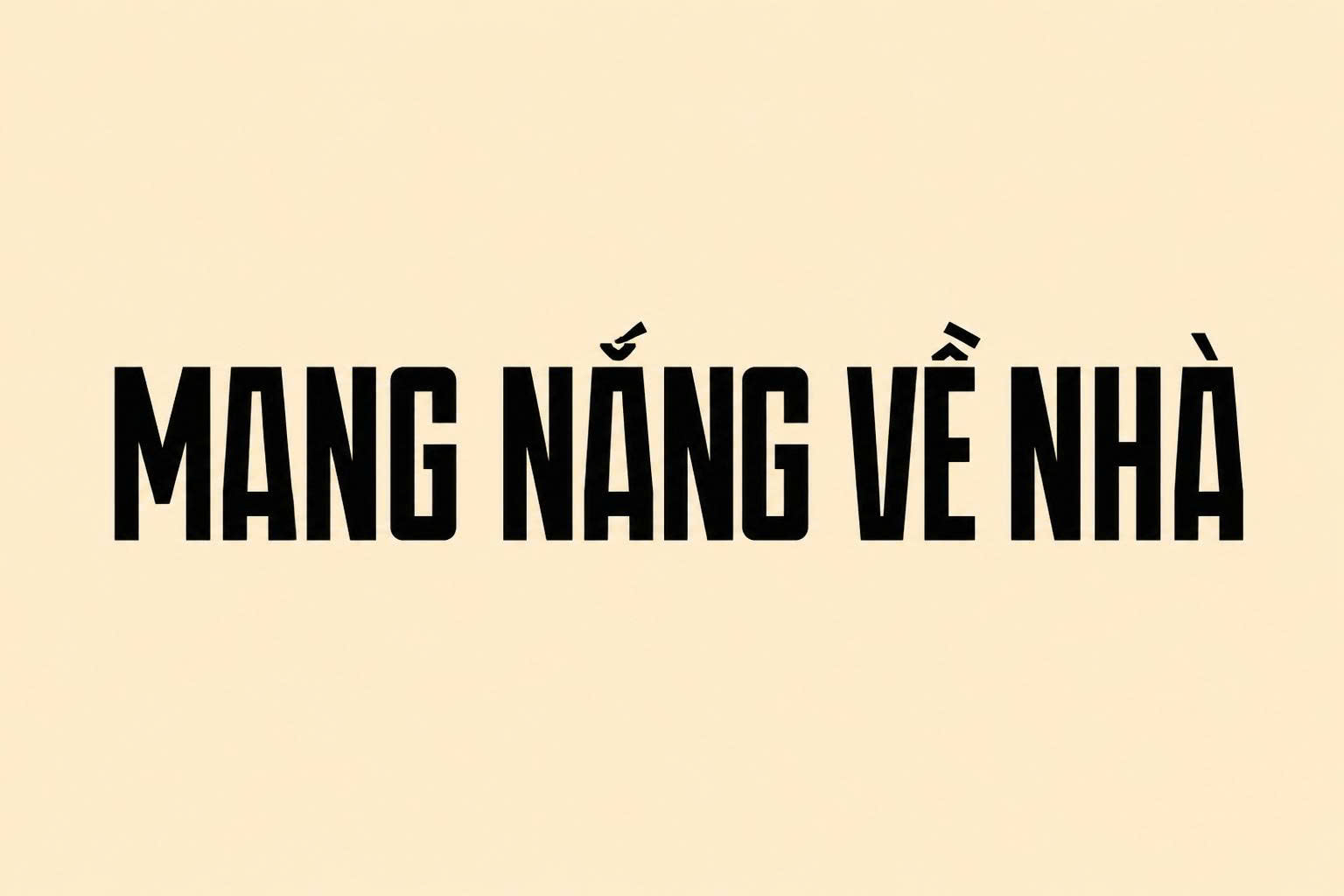
Hệ thống ký tự Cyrillic đặc thù
Bộ font tiếng Nga đầy đủ bao gồm các ký tự đặc biệt như “д”, “ж”, “щ”, “ю”… vốn không có trong hệ chữ Latinh. Khi thiết kế tem nhãn cho hàng xuất khẩu, việc sử dụng một bộ font “full” đảm bảo các thông tin kỹ thuật, bảng thành phần và hướng dẫn sử dụng được hiển thị chính xác 100%, tránh những sai sót pháp lý nghiêm trọng khi đưa sản phẩm ra thị trường quốc tế.
Tính tương thích đa ngôn ngữ (Multilingual Support)
Một bộ font cyrillic đầy đủ chất lượng cao thường được thiết kế theo chuẩn Unicode, hỗ trợ đồng thời tiếng Nga, tiếng Anh và tiếng Việt. Điều này cực kỳ quan trọng trong dàn trang bao bì song ngữ tại Việt Nam, giúp các khối văn bản đạt được sự đồng nhất về phong cách thiết kế (Typography Style), không bị hiện tượng “chữ đậm chữ nhạt” do phải dùng hai bộ font khác nhau.
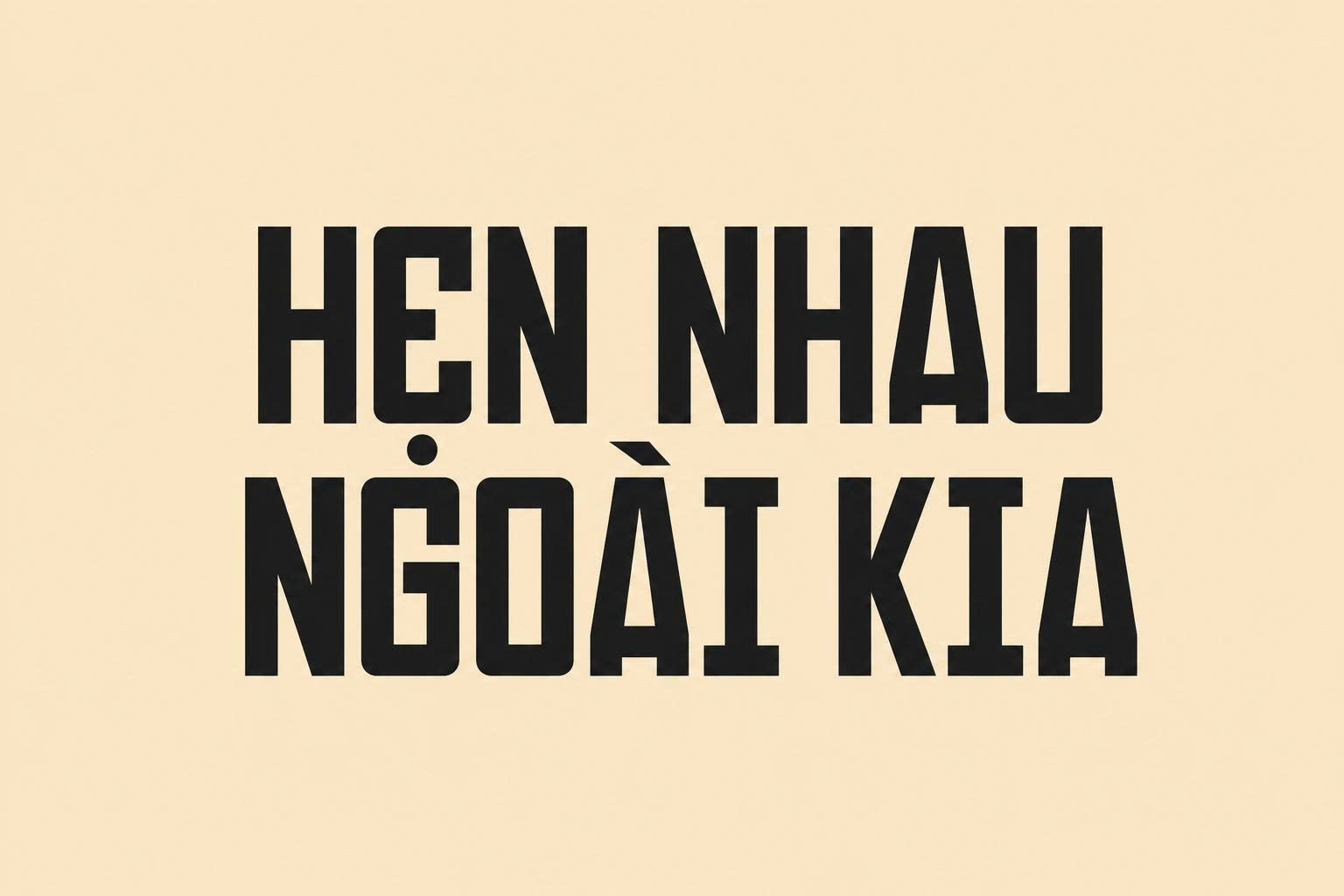
Tại sao cần sử dụng font tiếng Nga Việt hóa cho thiết kế bao bì?
Trong ngành sản xuất bao bì tại Doozypack.vn, chúng tôi thường xuyên xử lý các mẫu tem nhãn thực phẩm, mỹ phẩm xuất khẩu sang thị trường Nga. Việc sử dụng font tiếng Nga Việt hóa mang lại nhiều lợi ích:
- Đồng bộ nhận diện thương hiệu: Giúp tên thương hiệu và thông tin mô tả bằng tiếng Việt và tiếng Nga có cùng một diện mạo hiện đại hoặc cổ điển tùy theo định vị sản phẩm.
- Dễ dàng kiểm soát bố cục: Với phông chữ hỗ trợ cả hai ngôn ngữ, designer có thể căn chỉnh khoảng cách dòng (leading) và khoảng cách chữ (kerning) một cách chính xác trên toàn bộ nhãn mác.
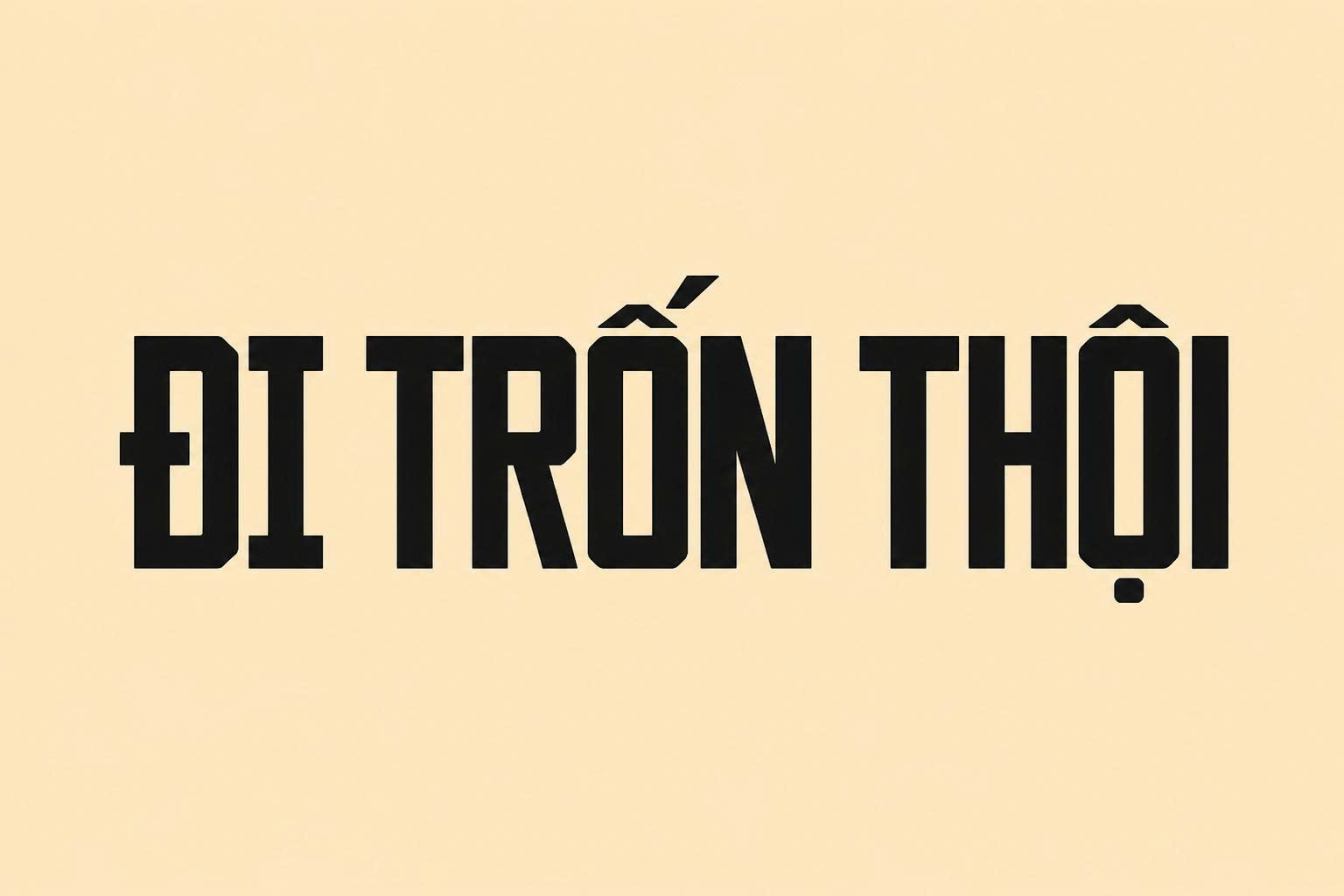
Doozypack.vn tổng hợp bộ thư viện font tiếng Nga đa dạng từ phong cách không chân (Sans-serif) hiện đại đến có chân (Serif) trang trọng, phù hợp cho mọi nhu cầu thiết kế.
| Nhóm Font | Đặc điểm thị giác | Ứng dụng đề xuất tại Doozypack.vn |
| Sans-serif Cyrillic | Hiện đại, minh bạch | Dùng cho bảng thành phần, mã vạch, thông số kỹ thuật. |
| Serif Cyrillic | Cổ điển, uy tín | Dùng cho tên sản phẩm cao cấp, nhãn rượu, hộp sâm. |
| Display Cyrillic | Nổi bật, cá tính | Dùng làm tiêu đề chính, slogan hoặc logo thương hiệu. |
Tư vấn từ chuyên gia: Khi thiết kế bao bì xuất khẩu, bạn nên ưu tiên các dòng Sans-serif (không chân) có độ dày trung bình (Medium). Đây là nhóm font an toàn nhất, đảm bảo người tiêu dùng bản địa dễ dàng đọc được thông tin ngay cả ở kích thước tem nhãn nhỏ.
- Hộp giấy quà tặng: Sự kết hợp giữa font tiếng Nga Việt hóa và kỹ thuật ép kim mờ tạo nên vẻ ngoài chuyên nghiệp cho các sản phẩm nông sản, cà phê xuất khẩu.
- Túi giấy doanh nghiệp: Tên công ty và địa chỉ in bằng font Cyrillic giúp tăng tính quốc tế và uy tín cho thương hiệu khi tham gia các hội chợ thương mại toàn cầu.
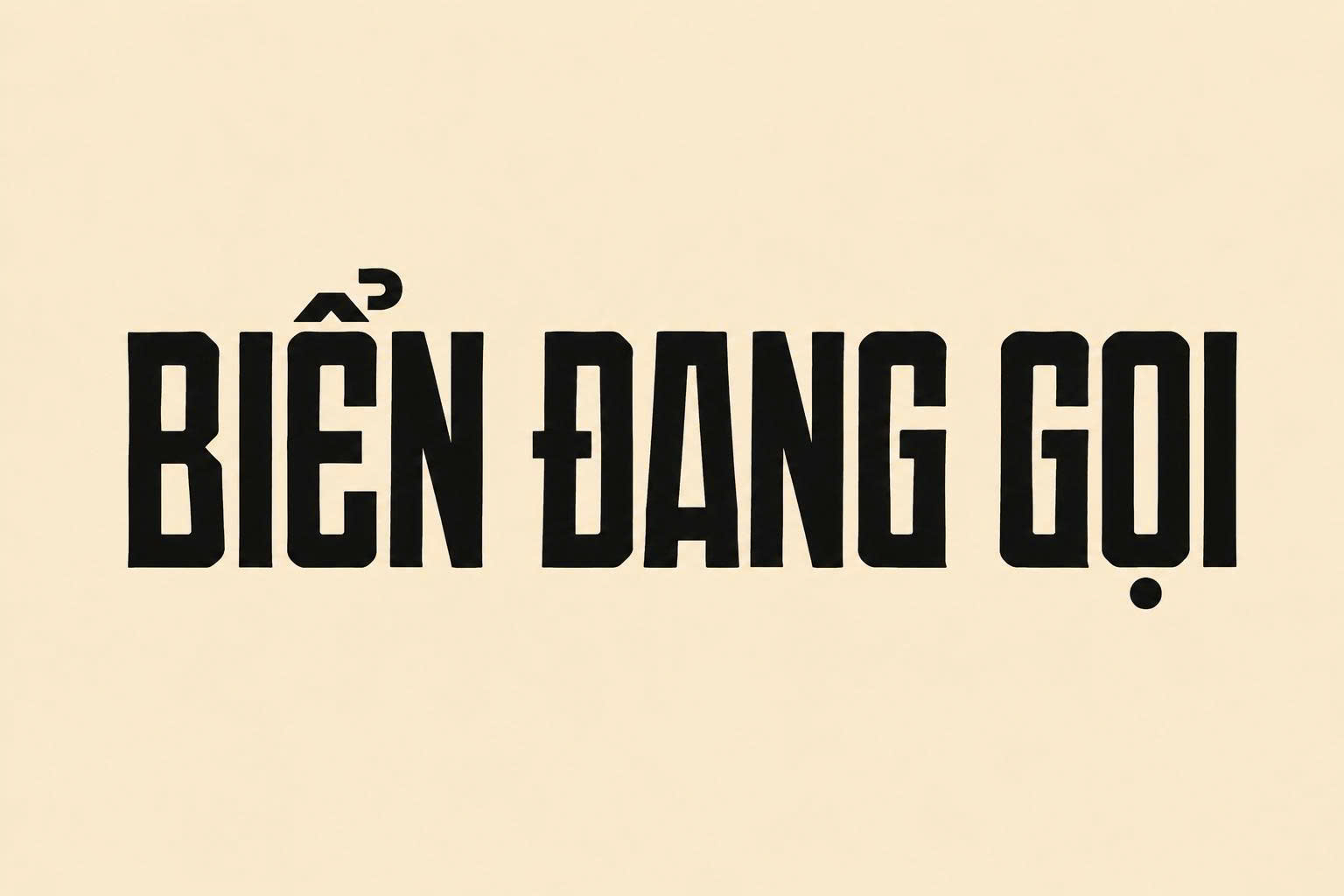
03 Lưu ý kỹ thuật khi dàn trang văn bản tiếng Nga (Cyrillic)
Sản xuất bao bì đa ngôn ngữ đòi hỏi designer cần lưu ý một số vấn đề kỹ thuật tại xưởng in chuyên nghiệp:
- Kiểm tra dấu câu đặc thù: Một số ký tự Cyrillic trông khá giống ký tự Latinh (như ‘P’, ‘H’, ‘B’) nhưng có ý nghĩa âm đọc hoàn toàn khác. Bạn cần sao chép văn bản gốc từ bản dịch chuẩn để tránh nhầm lẫn.
- Kích thước chữ tối thiểu: Do cấu trúc chữ Cyrillic thường phức tạp hơn chữ Latinh, hãy giữ size chữ tối thiểu từ 6.5pt trở lên để các nét chữ không bị dính vào nhau sau khi in Offset.